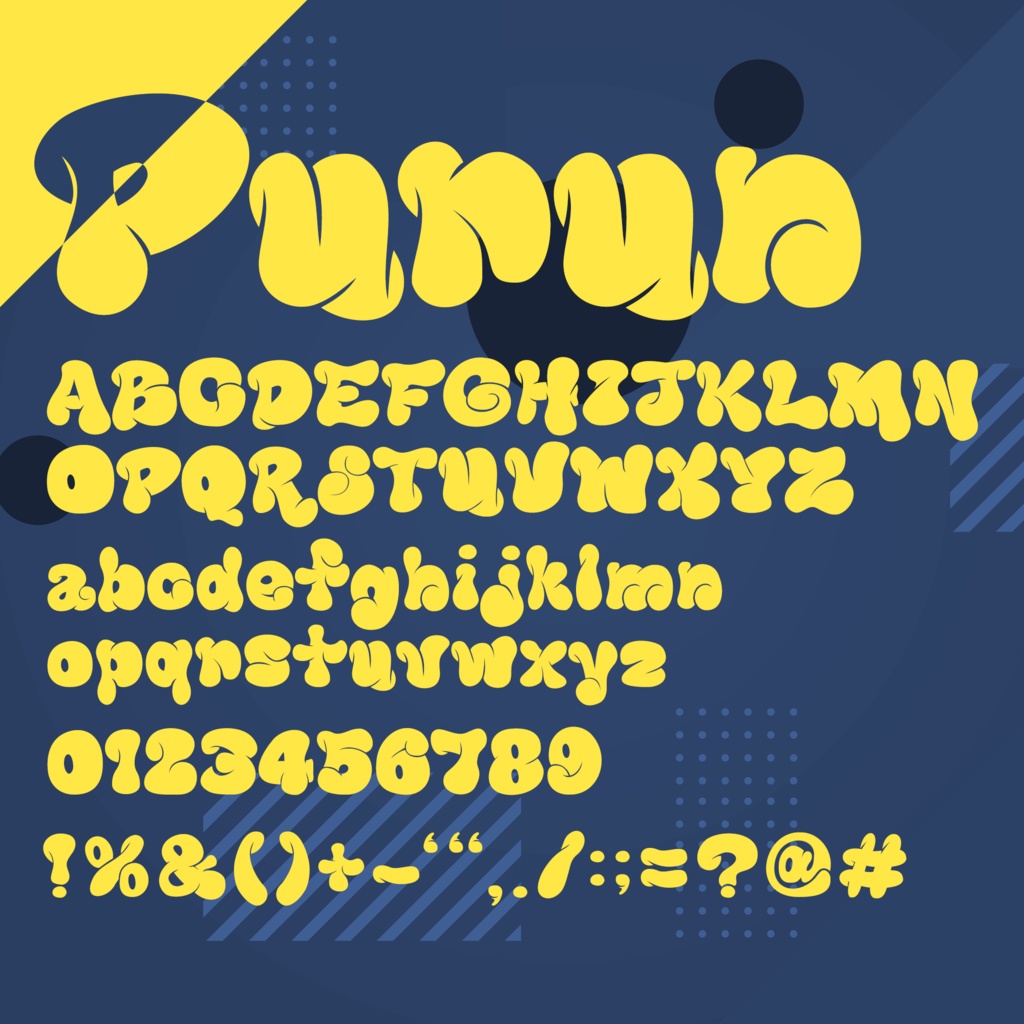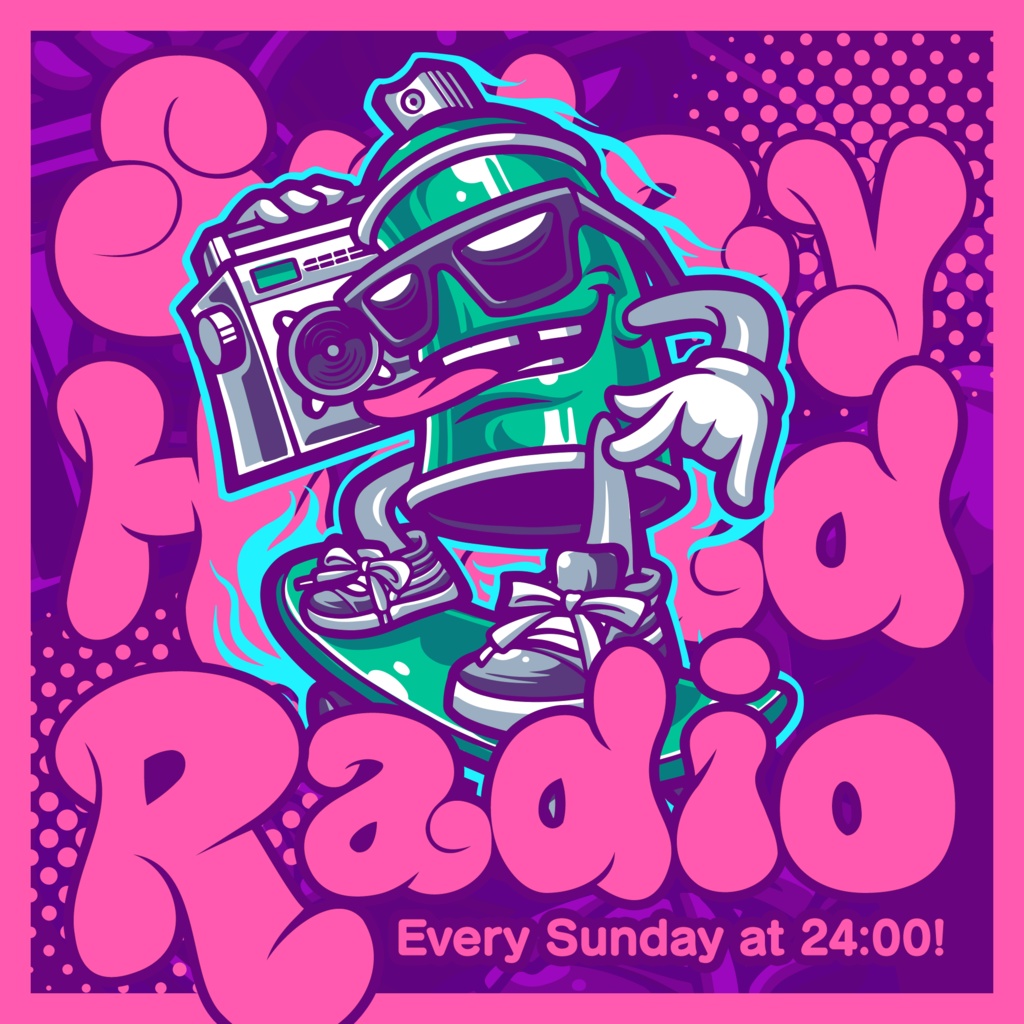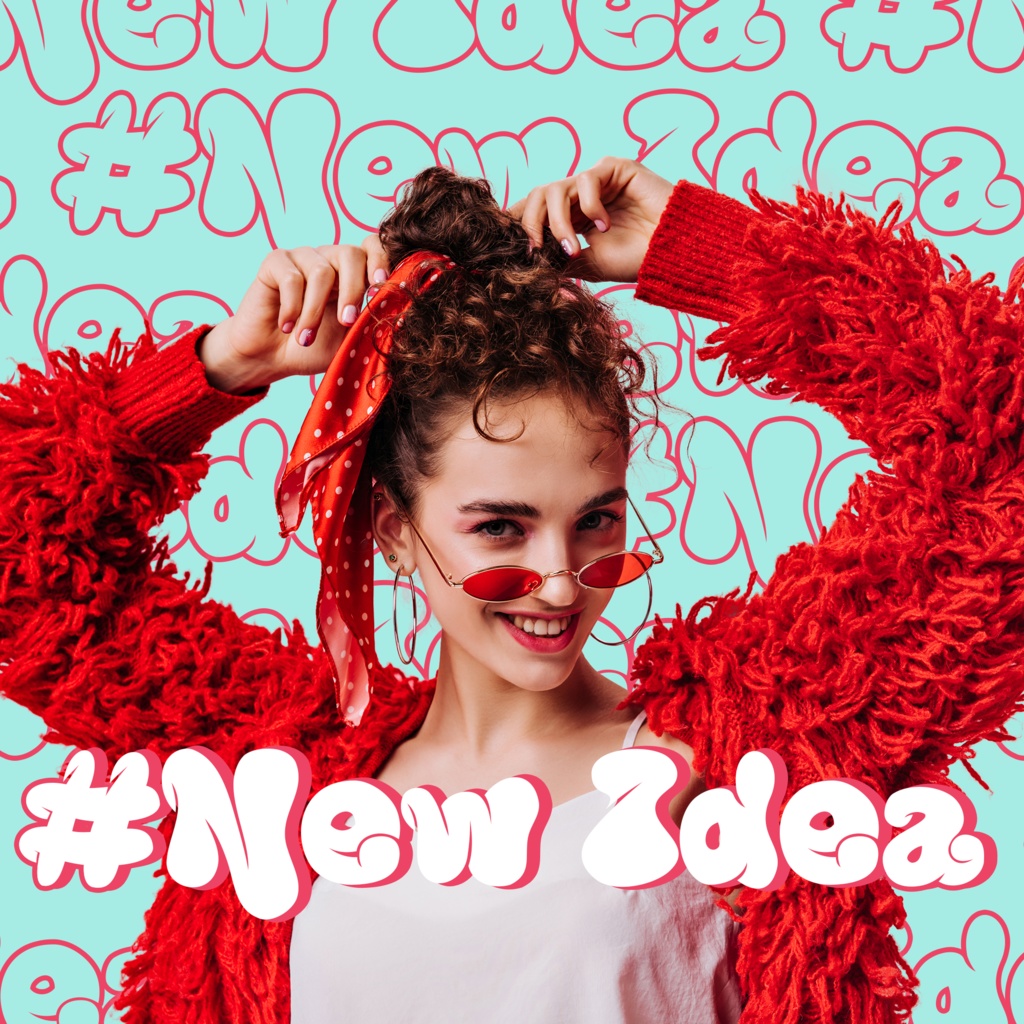
ポップでキュートなグラフィティフォント/Purun
Purunはストリートグラフィティをイメージしたポップでキュートな欧文フォントです。 特にかわいい系のデザインやグラフィティ風のデザインによくマッチします。 書体が太く、かつ細かいので本文よりも見出しでの使用がおすすめです。 英語の大文字・小文字、数字、約物、記号を収録しております。 気に入っていただけたらスキ!を押していただけると嬉しいです。 励みになります!